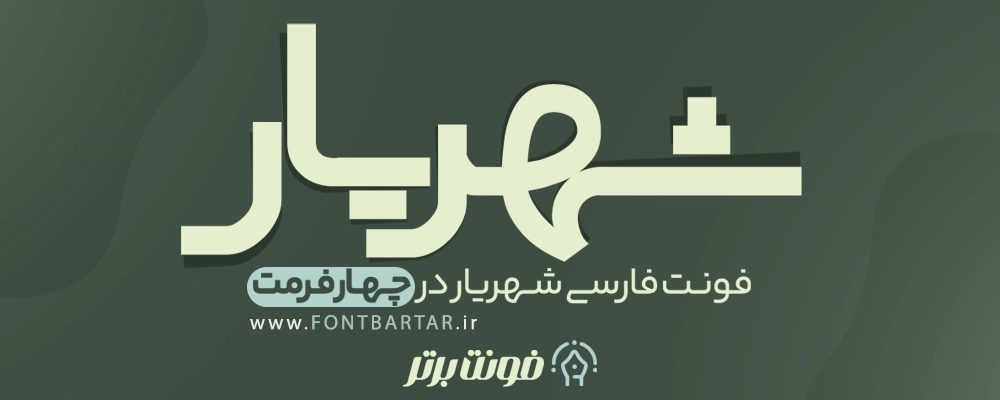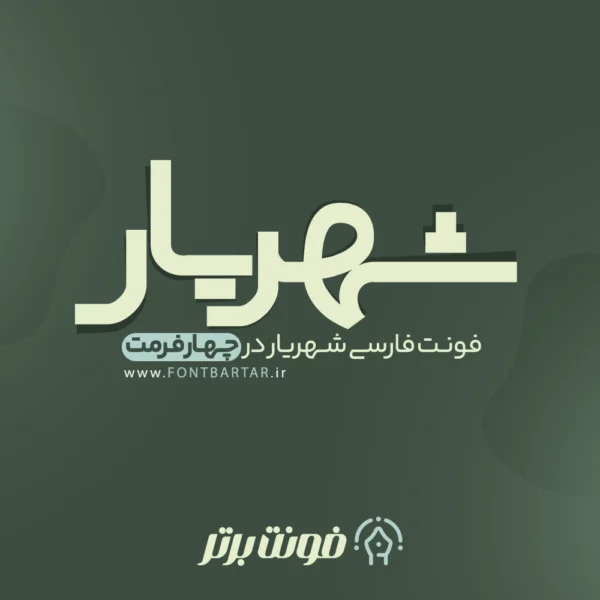
فونت فارسی شهریار
فونت شهریار
Shahriyar Font
فونت شهریار یک فونت فارسی زیبا و حرفه ای می باشد که عین زیبایی و حرفه ای بودن با سبکی ساده ولی خاص و متفاوت طراحی شده است. طراحان می توانید بهترین فونت تایپ را با قیمتی مناسب از سایت فونت برتر خریداری و در خلق آثار گرافیکی خود مورد استفاده قرار دهید. تایپ با فونت خاص شهریار از جمله فونت هایی می باشد که در تمامی طراحی های گرافیکی قابل استفاده می باشد و محدودیتی در استفاده از بهترین فونت تایپ فارسی وجود ندارد.
ویژگی های فونت زیبا شهریار:
• فونت زیبا و ساده – فونت تایپ فارسی
• فونت جالب و متفاوت
• مناسب انواع متون
• کیفیت مناسب و بالا
• فونت تایپ مناسب انواع طراحی گرافیکی